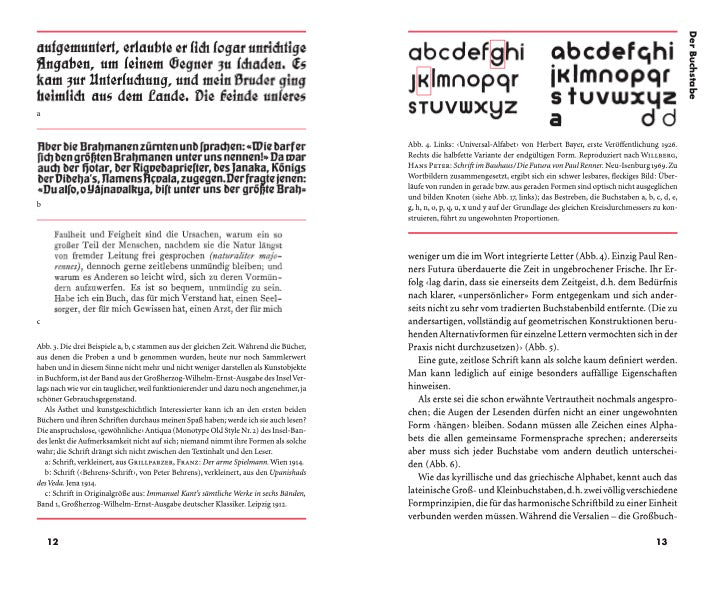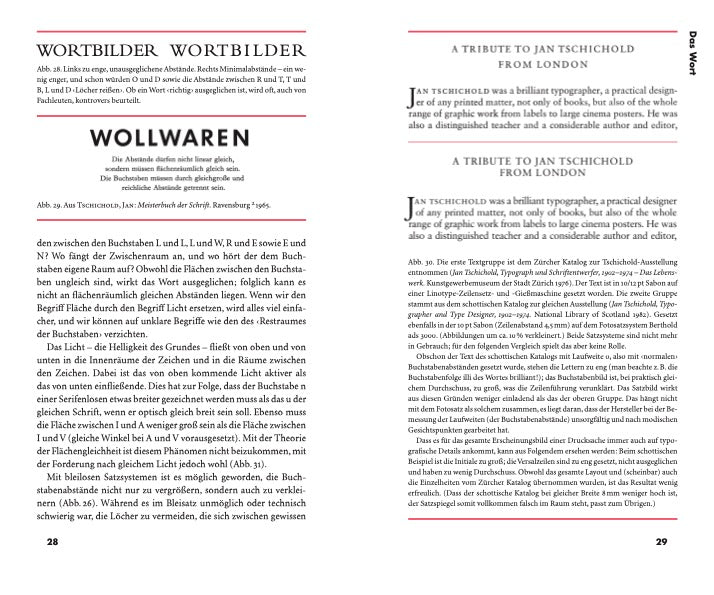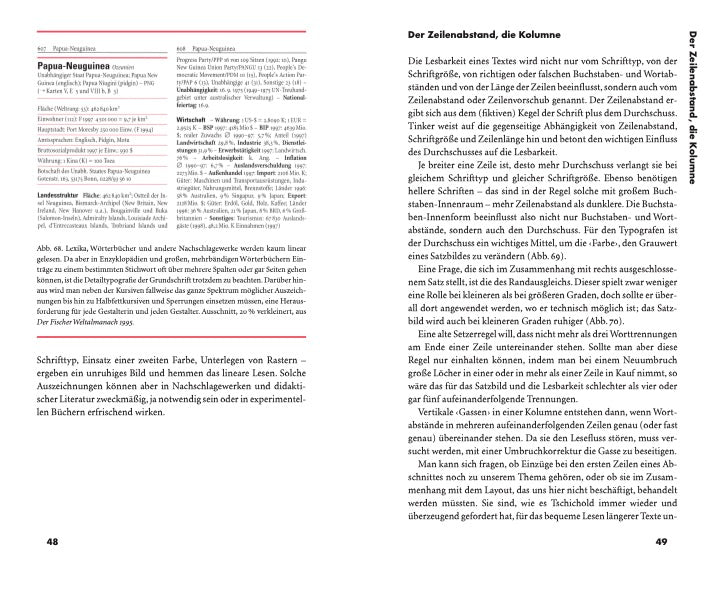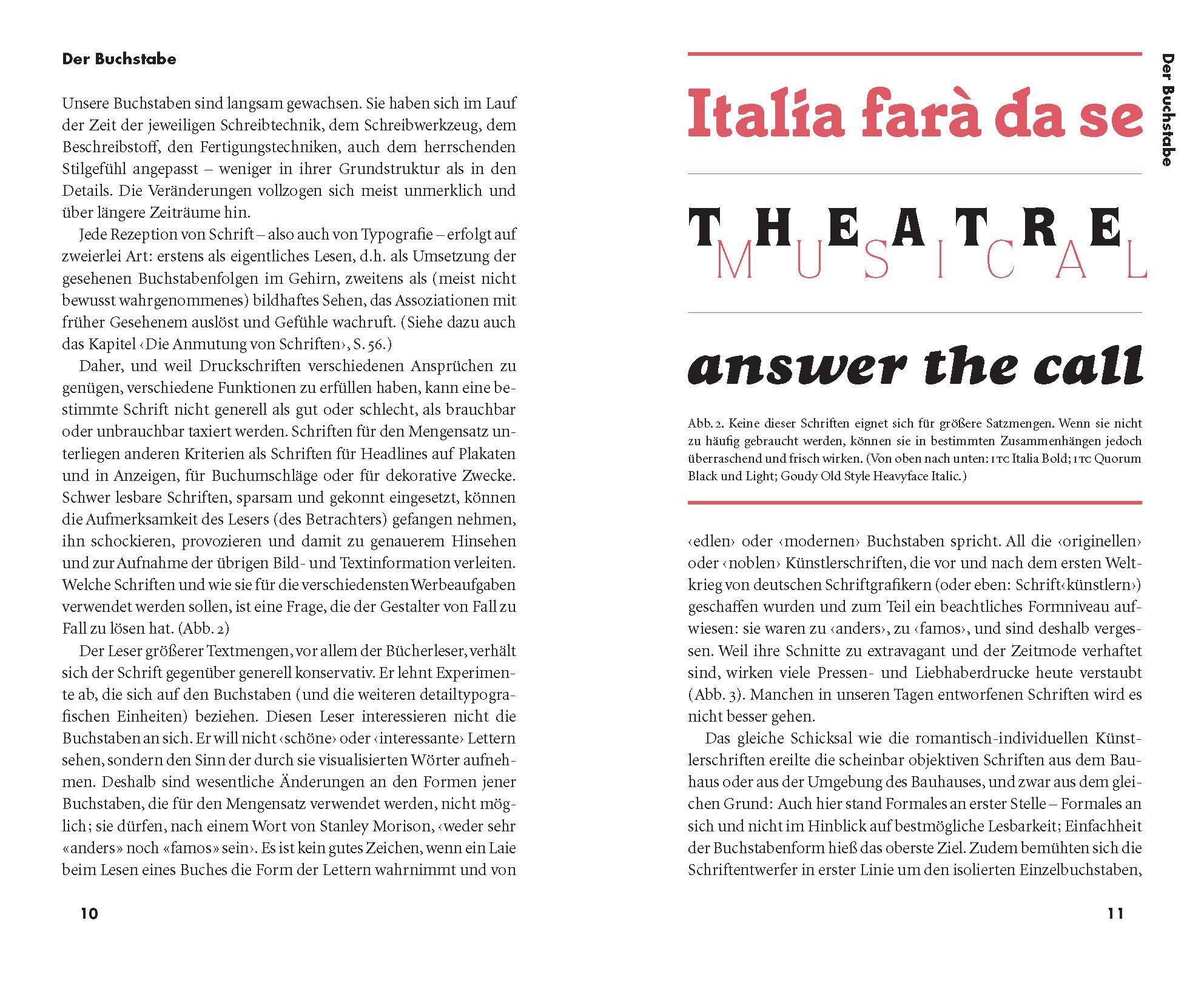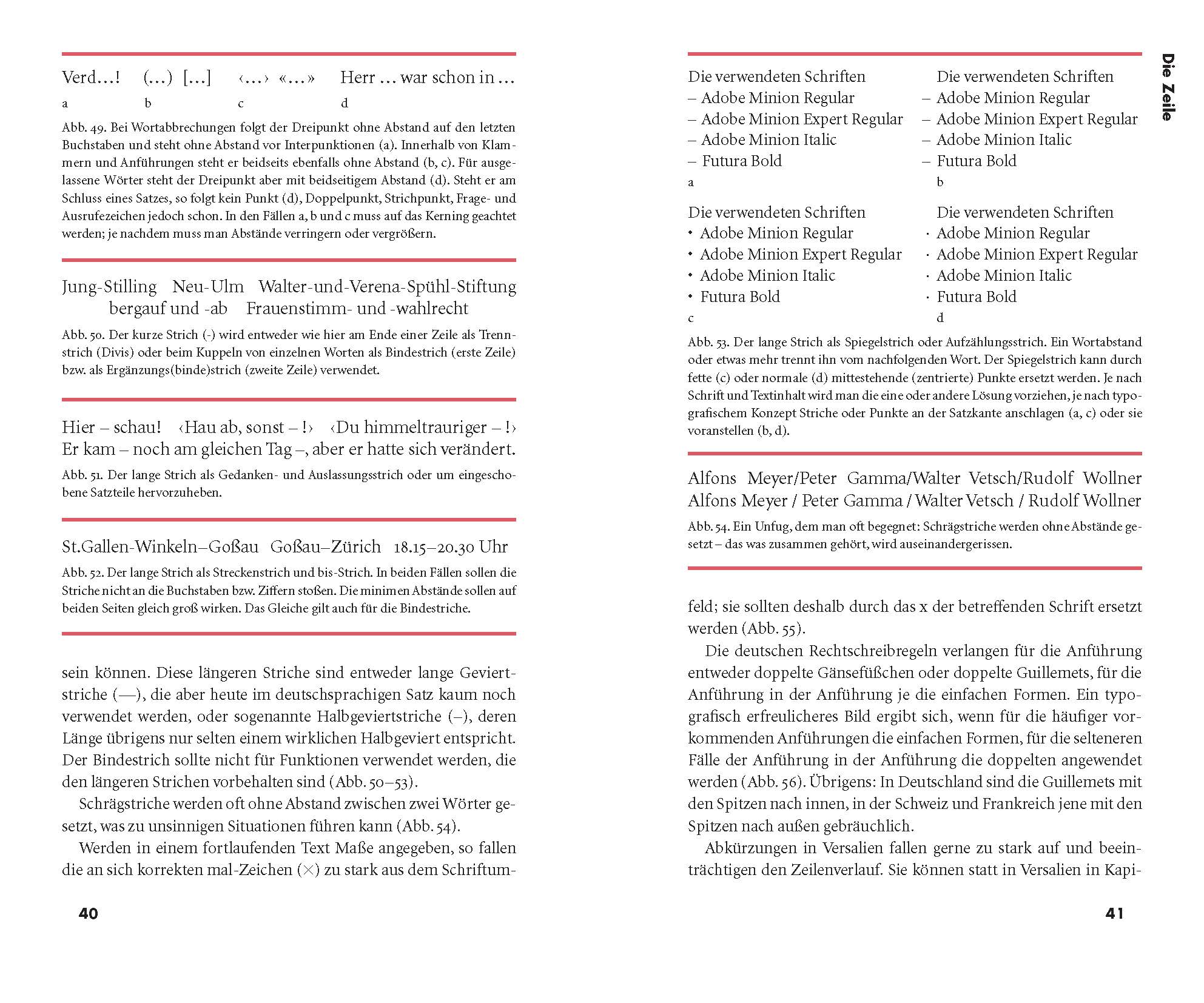
Das Detail in der Typografie
Der Schweizer Typograf und Buchgestalter Jost Hochuli gibt in dieser handlichen Broschüre eine knapp gefasste, informative Einführung in die Mikro- oder Detailtypografie. Im Zentrum stehen hierbei die grundlegenden Einheiten: Buchstabe, Buchstabenabstand, Wort, Wortabstand, Zeile, Zeilenabstand, Kolumne.
Ausgehend von den physiologischen und psychologischen Bedingtheiten des Lesevorgangs entfaltet der Autor auf anschauliche Weise die Grundelemente von Buchstaben und gesetzter Schrift, weckt den Sinn für die hier oft alles entscheidende Nuance anhand einer Fülle von Beispielen. «Das Detail in der Typografie» ist eine prägnante Darstellung all dessen, was jeder – ob Leser, Lektor, Redakteur, Typograf oder Buchgestalter – über die Grundlagen unserer Schrift und Lesekultur wissen sollte.